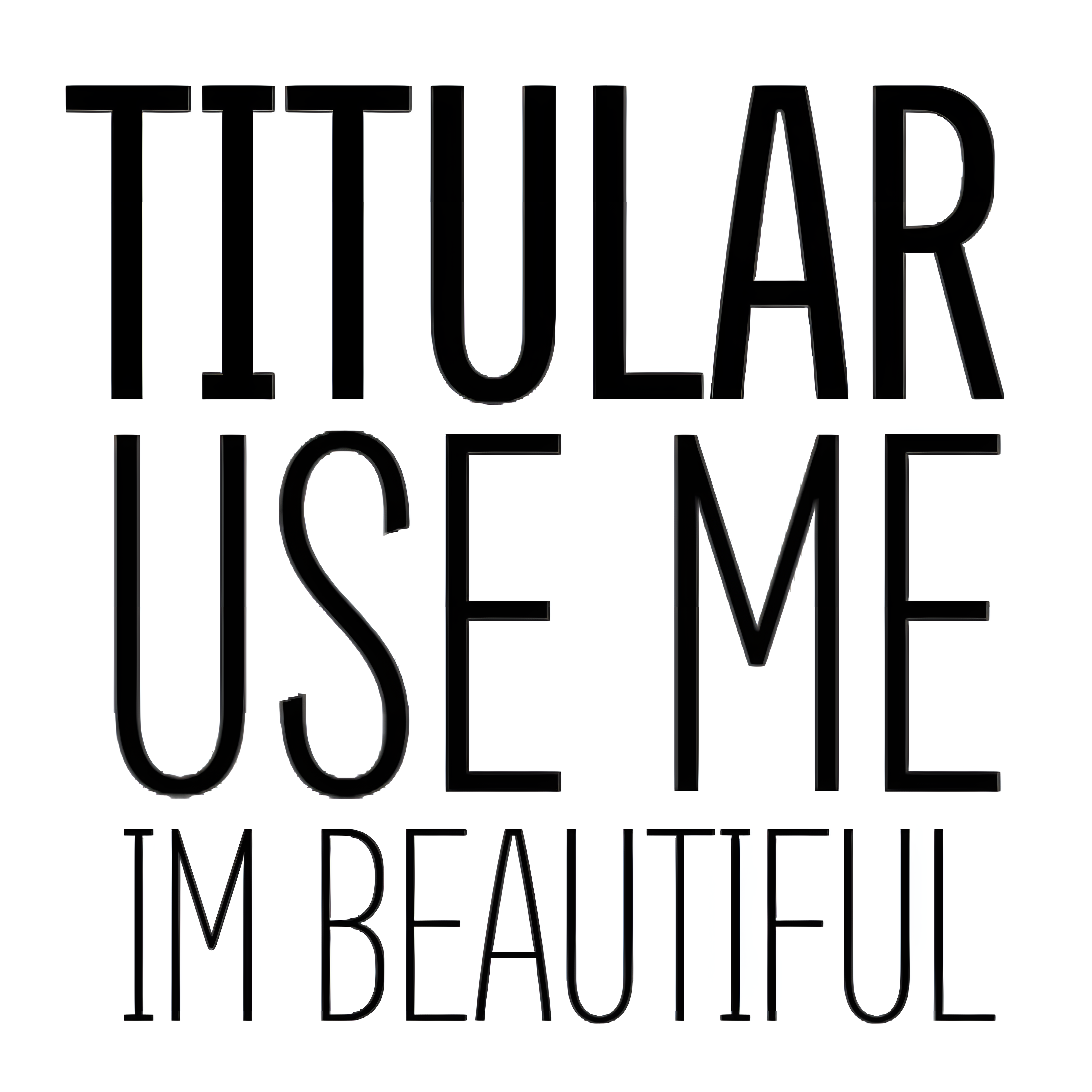
Titular
| Año | 2015 |
| Créditos | Daniel Hernández, Luciano Vergara |
| Descripción | Titular es una tipografía sans-serif condensada que funciona bien en títulos, subtítulos, periódicos, revistas, así como con logotipos, marcas y carteles. |